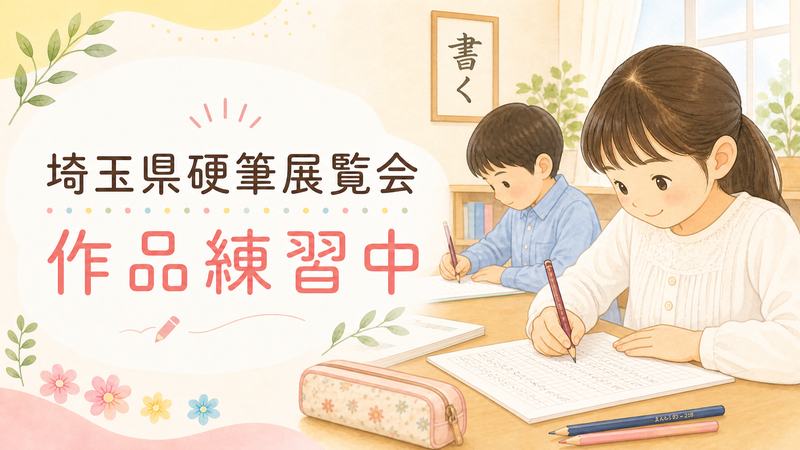
教室ではこの時期、埼玉県硬筆展覧会に向けた作品練習が始まっています。
毎年この季節になると、
「今年の課題は??いつから練習始まるの?」
「最後まで丁寧に書けるかな・・・」
と、子どもたちもワクワクドキドキ。
でも、最初から上手に書けなくても大丈夫。
硬筆展覧会の練習は、作品を仕上げるためだけの時間ではなく、一文字ずつ丁寧に見る力や、落ち着いて書く力を育てる時間でもあります。
今日は、教室での練習の様子と、子どもたちの成長についてお話ししたいと思います。
学年ごとに、がんばるポイントが違います
今年も埼玉県硬筆展覧会の課題は、学年によって大きく異なります。
低学年では、文字の形や大きさをそろえて書くことが大切になってきます。
中学年では、文章全体のまとまりや行の整いも意識していきます。
そして高学年になると、字形だけでなく、全体の読みやすさやバランスもより大切になります。
同じ「硬筆の練習」といっても、学年やその子の今の力によって、見ていくポイントはそれぞれ違います。
だからこそ教室では、一人ひとりに合わせながら、無理のない形で練習を進めています。
硬筆展覧会の練習で大切にしていること
作品づくりというと、
「きれいに書かなきゃ」
「上手に仕上げなきゃ」
と感じるお子さんもいるかもしれません。
もちろん、丁寧に書くことは大切です。
でも教室では、それだけを目標にしているわけではありません。
たとえば、
- 鉛筆の特徴や扱い方を知ること
- お手本の観察の仕方を知ること
- 文字の特徴を知ること
- どうしたらよく書けるのか考えること
こうしたことを大切にしながら取り組んでいます。
いきなり全部を完璧に覚えて書くのは、なかなか難しいものです。
だからこそ、
「よく考えながら」
「お手本を見ながら」
というように、声かけをして小さなステップを重ねながら進めています。
練習の中で見えてくる子どもたちの成長
硬筆展覧会の練習では、子どもたちの成長がいろいろな場面で見えてきます。
最初は文字数の多さにびっくりしたり、
「むずかしそう」
と感じたりする子もいます。
でも、何回か書くうちに、
- お手本をよく見るようになった
- 一画一画を意識できるようになった
- 自分で直したいところに気づけるようになった
という変化が少しずつ出てきます。
見た目の仕上がりだけでは分かりにくくても、その子なりの前進はちゃんとあります。
教室では、そうした小さな「できた」を見つけながら、声をかけることを大切にしています。
その積み重ねが、字を書くことへの自信にもつながっていくのだと思います。
ご家庭でも見ていただきたいこと
この時期は、ご家庭でも作品練習の話題が出ることがあるかもしれません。
そんなときは、結果だけでなく、取り組む姿にも目を向けていただけたらうれしいです。
たとえば、
「前より丁寧に書いているね」
「よく集中していたね」
「がんばってお手本見ながら書いていたね」
そんなひと言が、お子さんの励みになることがあります。
硬筆展覧会は、どうしても「周りの作品と比べて上手に書けているか」に目が向きやすい行事です。
でも、丁寧に向き合った経験そのものが、お子さんの力になっていくのだと思います。
一人ひとりの一歩を大切にしながら
教室での硬筆展覧会の練習は、毎年同じように見えても、一人ひとり違います。
すぐにコツをつかむ子もいれば、少しずつ自分のペースで進む子もいます。
得意なことも、時間のかかるところも、それぞれ違っていて当然です。
だからこそ、もじもじでは「みんな同じように」ではなく、その子にとっての一歩を大切にしています。
作品づくりを通して、字が整うことはもちろん、
「もう少しがんばってみよう」
「前よりよく書けた」
そんな気持ちも育っていってくれたらうれしいです。
おわりに
埼玉県硬筆展覧会に向けた練習は、子どもたちにとって少し緊張もある時間ですが、その中で見えてくる成長もたくさんあります。
これからも教室では、一人ひとりのペースを大切にしながら、安心して取り組めるように見守っていきたいと思います。